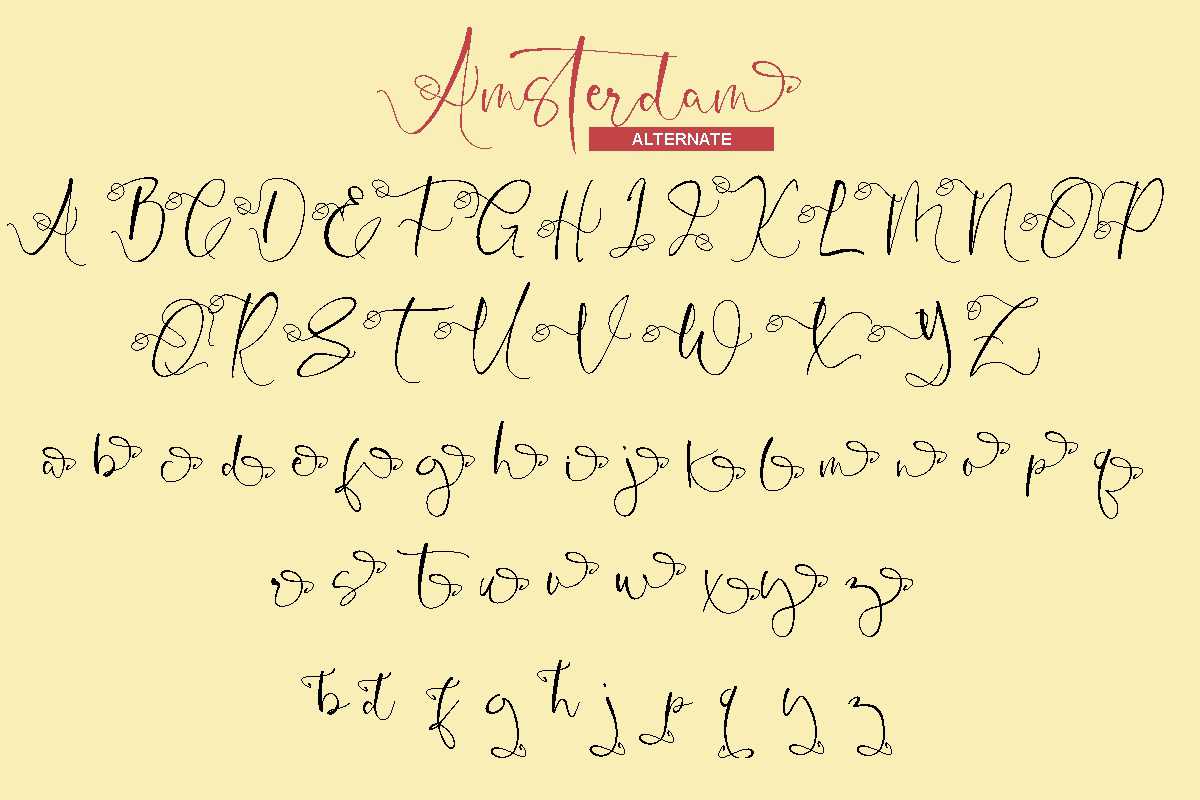
AmsterdamFontIsofa采用全新、现代和笔划的手写字体。该字体上添加了各种可选字符。该字体适用于徽标、时尚、文具、杂志、菜单、书籍、邀请函、问候卡、包装、标签、服装、营销、名片、,AmsterdamFontIsofa采用全新、现代和笔划的手写字体。该字体添加了各种可选字符。该字体适用于徽标、时尚、文具、杂志、菜单、书籍、邀请、问候卡、包装、标签、服装、营销、名片等。